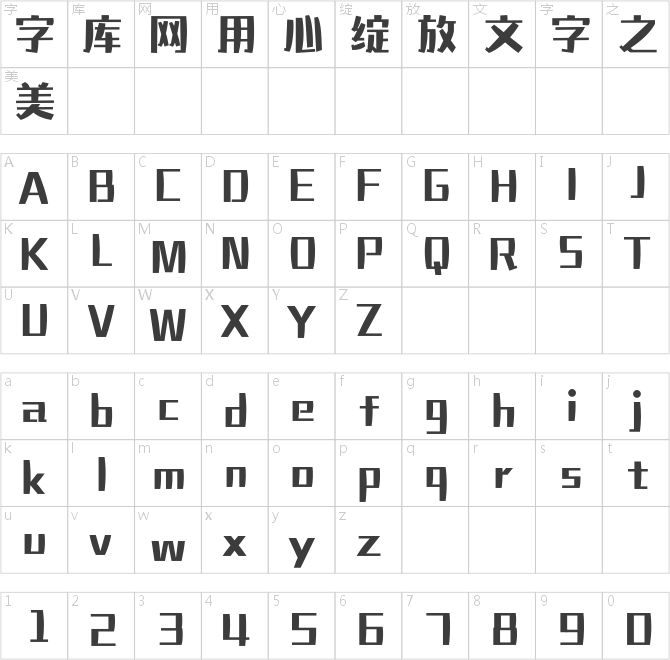
漢儀鑄字葫蘆娃簡 詳情頁
字體名稱: 漢儀鑄字葫蘆娃
漢儀鑄字葫蘆娃簡
漢儀鑄字葫蘆娃簡字體字庫是一款讓人賞心悅目、百看不厭的中文字體,適合各類廣告和產(chǎn)品包裝設(shè)計應(yīng)用,字體大小2.05MB,格式為ttf字體,上傳用戶是Me / ,yD ,作者/版權(quán)方為漢儀字庫